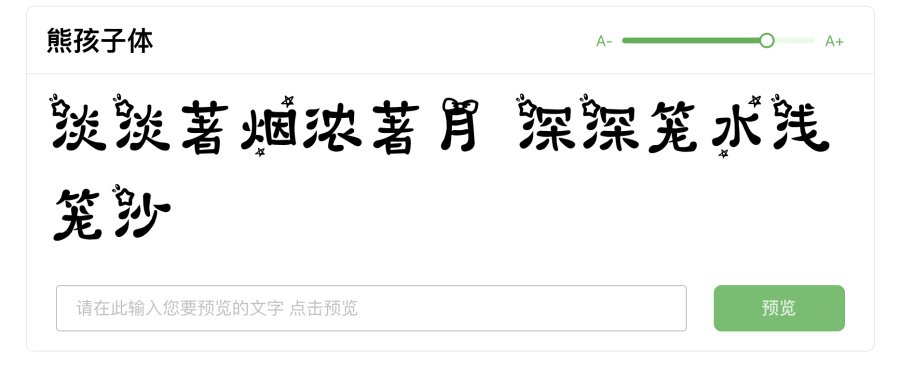
什么是艺术字体,我们怎么把艺术字体下载打包使用?
艺术字体是一个带有个性鲜明代表的字体,它的重要表现形式和意义就在于给人不一样的新颖和创新感觉。艺术字你可以说是涂鸦POP文字,也可以称之为美术字的异形设计。我们可以把字体视界的艺术字体下载打包,通过电脑输入后将这样一个传统的正规的字体,从它开始演变而来,通过特殊化和美化,通过细节的修饰,形成新一代带有形态美的涵义语言字。